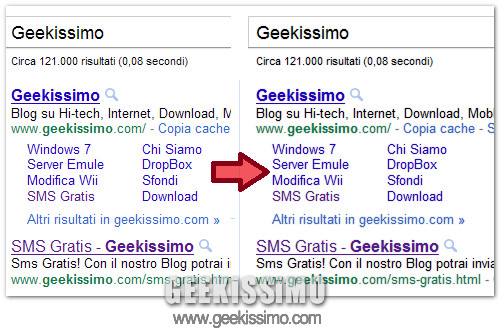
Dopo aver provato Safari su Mac e aver visto il modo spettacolare, chiaro e arrotondato, in cui vengono riprodotti i caratteri di scrittura, avete difficoltà a leggere i caratteri un po’ più sbiaditi di Firefox su Windows? Comprensibile, ma per fortuna c’è una soluzione.
Utilizzando l’estensione Stylish e un userstyle compatibile con quest’ultimo è possibile aumentare la leggibilità dei caratteri in Firefox senza stravolgerli troppo e senza snaturare lo stile delle pagine Web visualizzate con il browser del panda rosso.
- Questa la procedura da mettere in atto per rendere più “sexy” i caratteri di scrittura delle pagine Web visualizzate in Firefox:
È fatta! Adesso la leggibilità dei caratteri in Firefox dovrebbe essere nettamente migliorata (o quantomeno somigliante al font smoothing di Mac OS X). I cambiamenti sono visibili su tutti i siti Internet visitati, ma l’userstyle si può disabilitare facilmente all’occorrenza. Basta fare click destro sull’icona di Stylish presente nella barra di stato di Firefox e togliere la spunta dalla voce Font “Smoothing”.
Nel caso in cui vorreste qualcosa di ancora più “spinto” e di ancora più somigliante al rendering dei fonts su Mac OS X, provate l’userstyle Firefox Strong Font Rendering (Like Safari) rintracciabile su questa pagina.